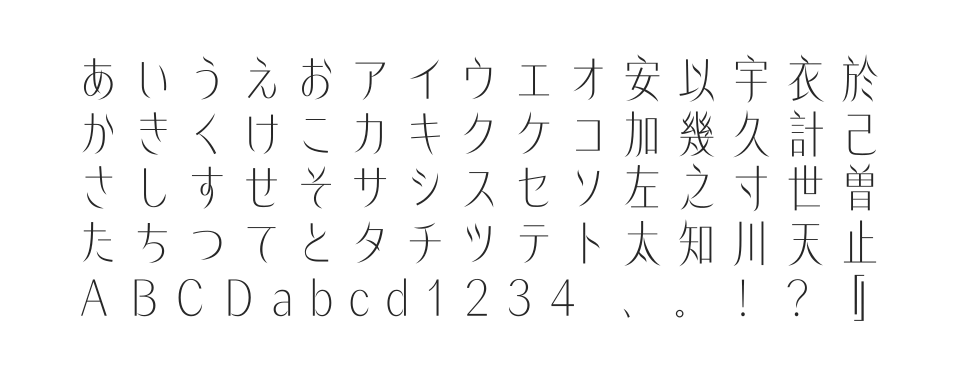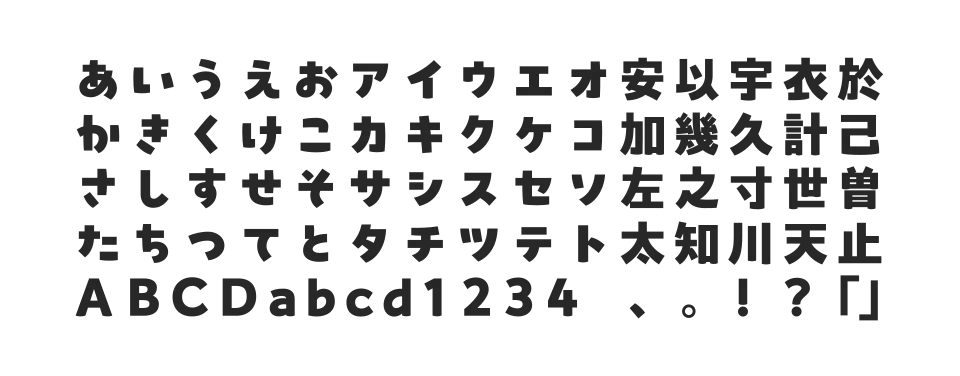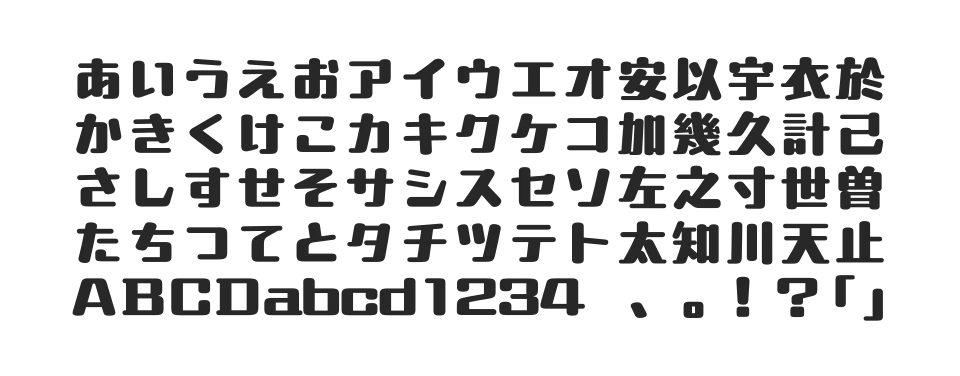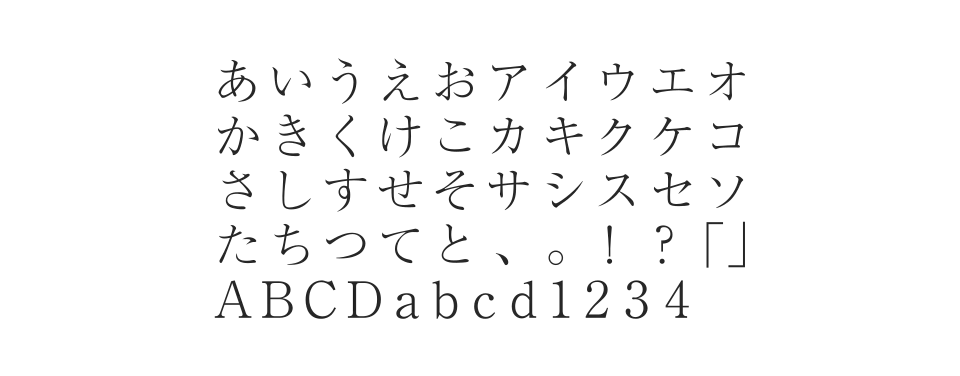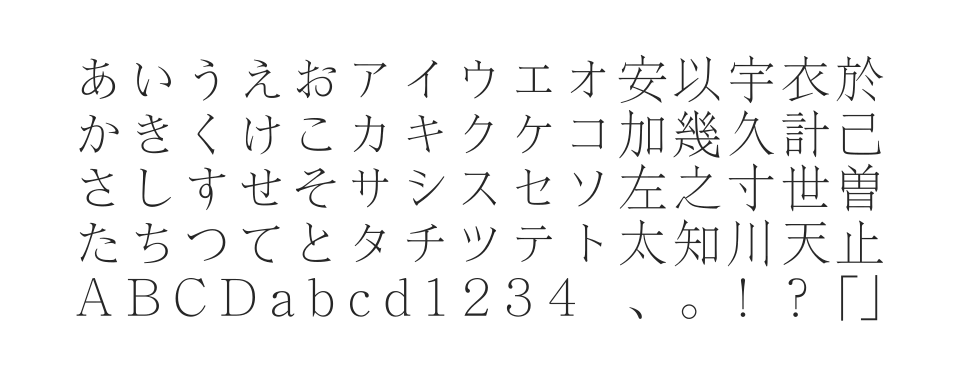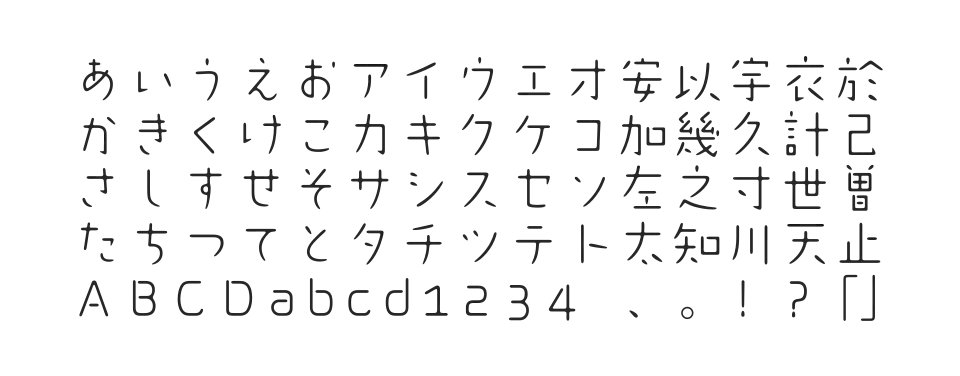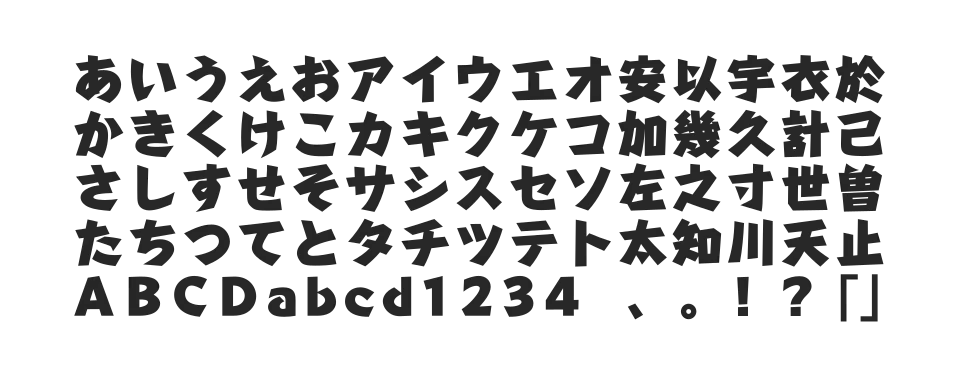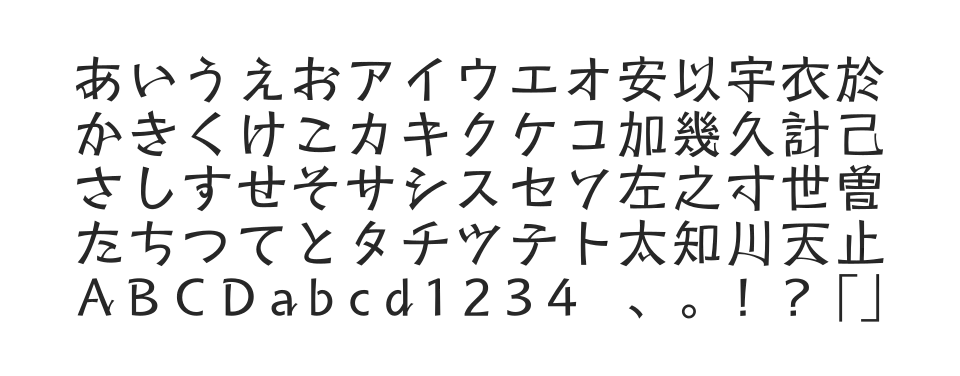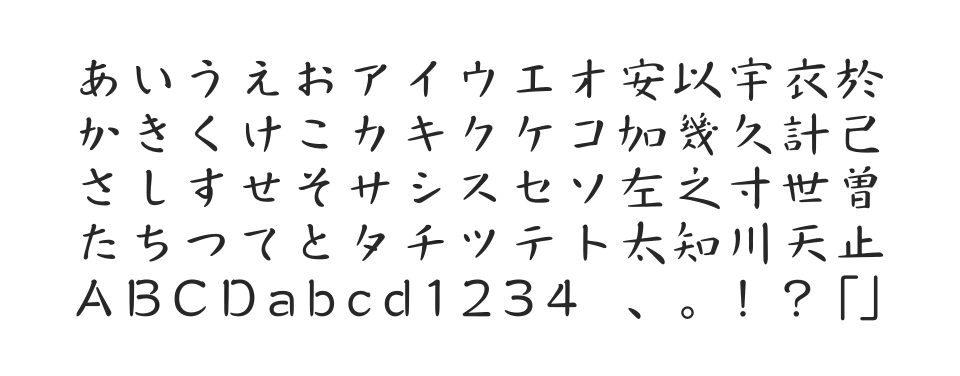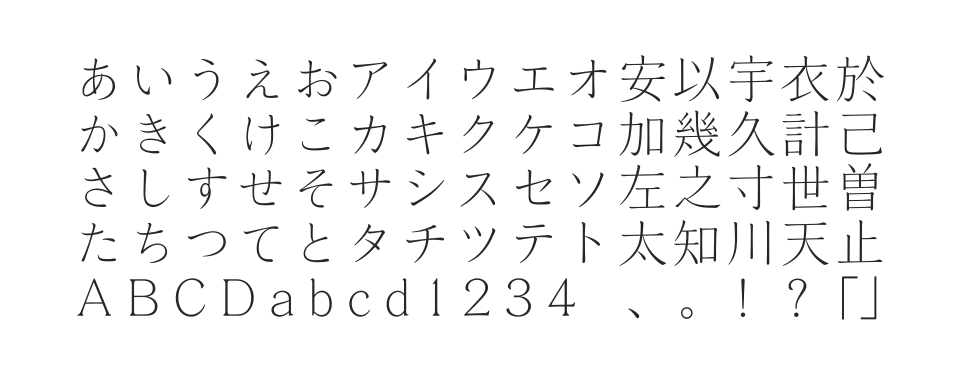
明朝体に楷書体や宋朝体の筆勢を加味したオリジナリティ豊かな書体。優しいタッチの流麗なエレメントと自然な構成で華奢でエレガントな表情を演出します。
エレガントで洗練されたデザインが特徴的な書体。上品な印象を与える文字デザインで、高級感のある表現に適したフォントです。
蜘蛛の糸を想起させる線が斬新なデザイン書体。文字中心のデザインでも動きのある勢いを演出できる、個性的な表現が可能なフォントです。
クラフト感のあるデザインが特徴的な手作り風フォント。温かみと親しみやすさを兼ね備えた、カジュアルなシーンに適した書体です。
学園をイメージした親しみやすいデザインのフォント。教育関連や若年層向けのコンテンツに適した、温かみのある書体です。
モリサワの新書体として展開された中国語対応の明朝体フォント。繊細で美しい文字デザインが特徴的な書体です。
森川龍文堂明朝体をベースに開発されたスタンダードな明朝体。金属活字に由来する彫刻刀の冴えを活かした、DTPの基本書体として幅広く使用される定番フォント。
2023年モリサワ新書体として発表された個性派デザイン書体。見出しやロゴに最適で、モダンで洗練されたデザインが特徴的なフォントです。
太ゴシック体風のポップで可愛いフォント。かな文字は愛嬌があって遊び心が含まれたデザインで、濁点に丸の形を当てはめた個性的な書体です。
風、舞い落ちる葉、揺れるススキなど自然をモチーフにして設計されたデザイン書体。涼やかで洗練された印象を与える繊細でシャープなラインが特徴。